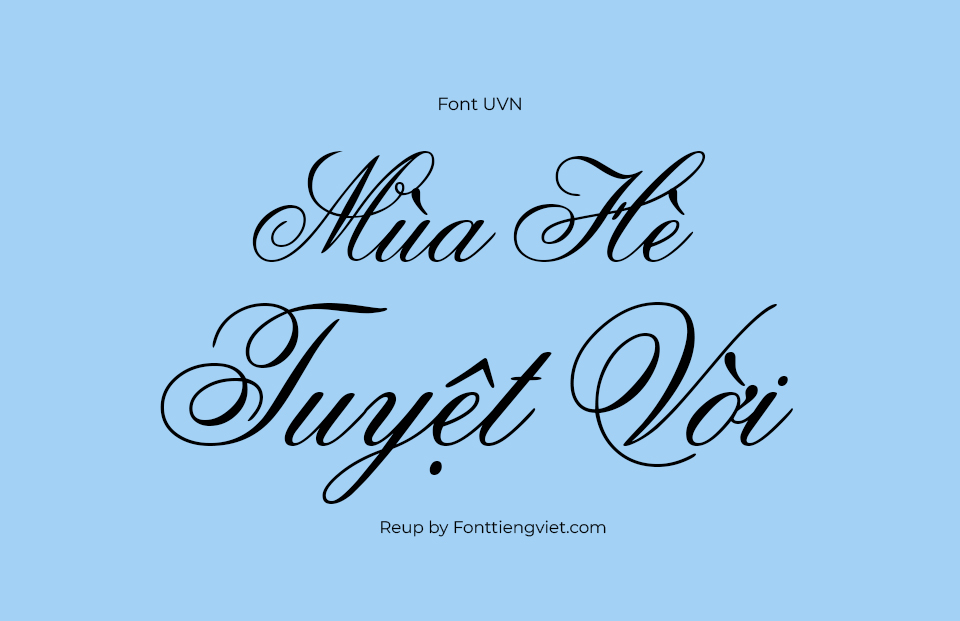
Trong thế giới thiết kế đồ họa Việt Nam, việc tìm kiếm một bộ chữ vừa mang nét cổ điển vừa thanh lịch là điều vô cùng quan trọng. Font Việt Hóa UVN Buc Thu chính là lựa chọn hoàn hảo dành cho những ai yêu thích vẻ đẹp của những bức thư tay truyền thống. Đây là một mẫu Font Miễn Phí được tinh chỉnh kỹ lưỡng để hỗ trợ đầy đủ tiếng Việt, giúp người dùng không còn lo lắng về lỗi font khi soạn thảo văn bản hay làm bài tập lớn. Với những đường nét mềm mại và bay bổng, font chữ này gợi lại ký ức về những nét bút mực trên trang giấy trắng, tạo nên sự gần gũi và đầy cảm xúc cho người xem.
Ưu điểm nổi bật của Font Việt Hóa UVN Buc Thu
Thiết kế tinh tế và chuyên nghiệp
Đặc điểm lớn nhất của Font Việt Hóa UVN Buc Thu chính là sự mô phỏng chân thực nét chữ viết tay. Các ký tự được thiết kế với độ nghiêng vừa phải, tạo cảm giác thanh thoát nhưng vẫn đảm bảo tính dễ đọc. Điều này cực kỳ phù hợp cho các em học sinh khi thiết kế thiệp chúc mừng, làm báo tường hoặc các giáo viên trang trí bài giảng điện tử thêm phần sinh động. Sự hài hòa giữa các nét thanh và nét đậm giúp tổng thể văn bản trở nên nghệ thuật hơn bao giờ hết.
Khả năng tương thích đa dạng
Cách sử dụng Font Việt Hóa UVN Buc Thu hiệu quả